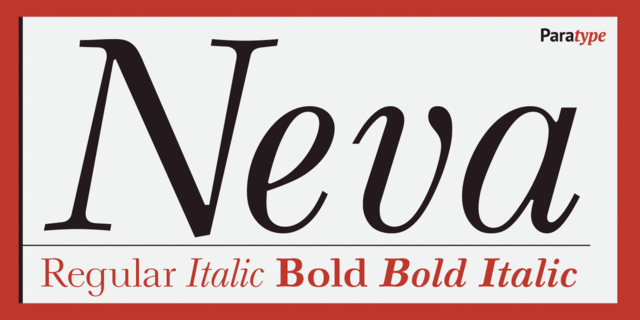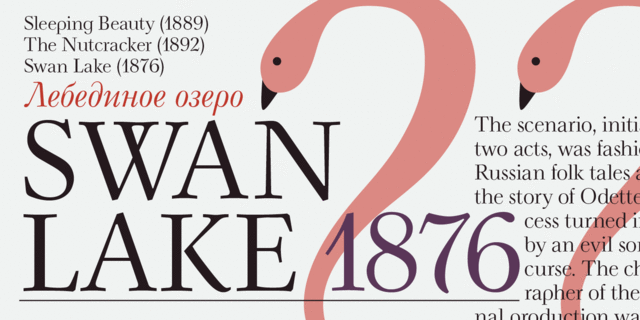
Neva (4 шрифта)
Гарнитура Нева в 2-х начертаниях для строкотливного и крупнокегельного набора была разработана в 1970 году в Отделе наборных шрифтов НПО Полиграфмаш художником книги Павлом Кузаняном (1901-1992). Шрифт создан на основе простых, строгих форм русской шрифтовой классики. На международном конкурсе имени Гутенберга в 1971 году шрифт Нева был отмечен почетным дипломом. Предназначен для набора художественной литературы и изданий по искусству, а также для акциденции. Цифровая версия и жирные начертания созданы для фирмы ParaType в 2002 году (дизайнер Любовь Кузнецова).